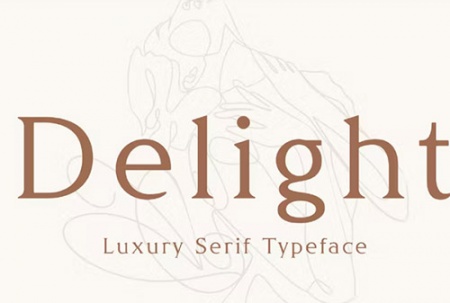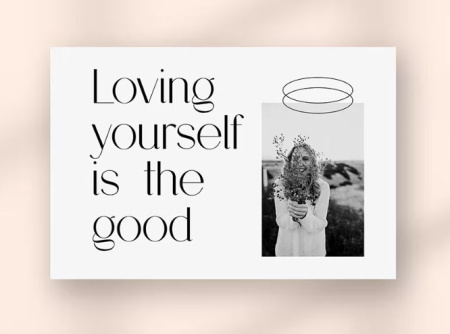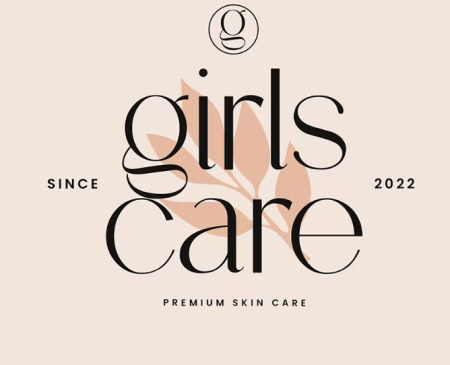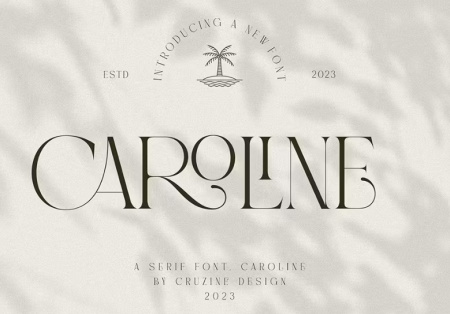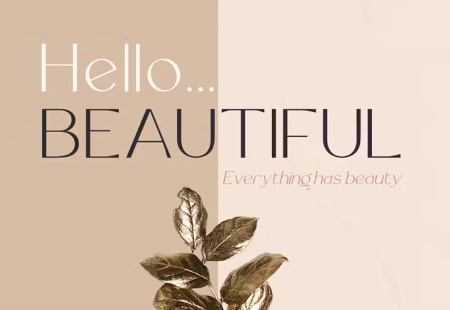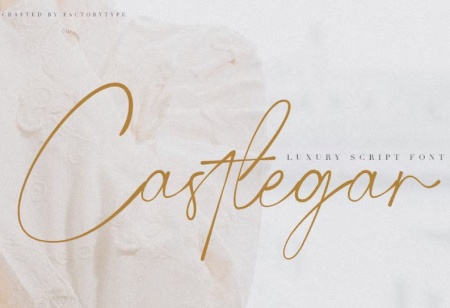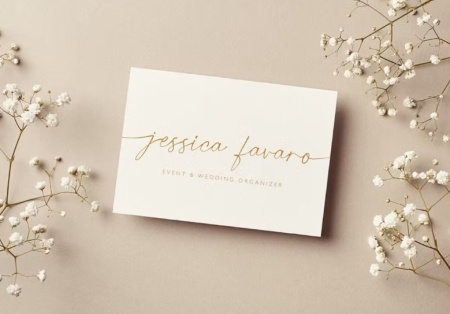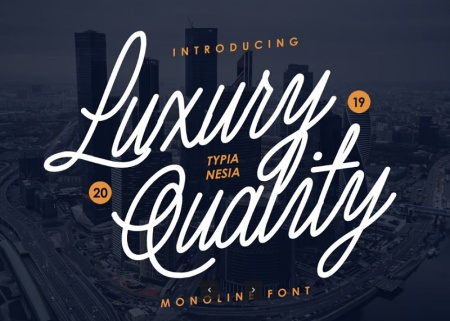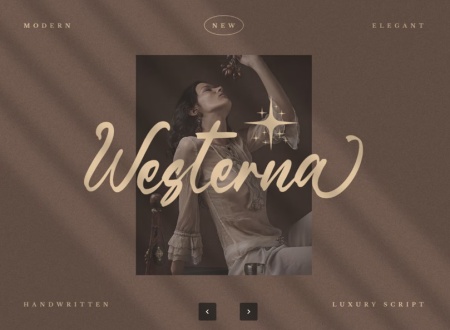
11 فونت لاکچری انگلیسی برای اینشات و کامپیوتر آپدیت جدید
دانلود فونت لاکچری انگلیسی Bonnevarc
در این پست از سایت gfx با معرفی یک فونت انگلیسی لاکچری جدید با نام Bonnevarc Luxury Sans Serif Font با شما همراه هستیم. فونت مدرن Serif که ظاهری زیبا، شیک و خاص دارد. این فونت لاکچری برای پروژههای مختلف مانند امضا، لوازم التحریر، لوگو، عروسی، نقل قولهای تایپوگرافی، جلد مجلات یا کتابها، سربرگهای وبسایت، لباس، برندسازی، طراحی بستهبندی و موارد دیگر کاملاً مناسب است. همچنین، برندسازی مرتبط با مد یا طراحی سرمقاله، ویژگیهای مردانه و زنانه را نشان میدهد. برای دانلود فونت لاکچری Bonnevarc به ادامه مطلب مراجعه کنید.
دانلود فونت انگلیسی ظریف و لاکچری Delight در جی اف ایکس دانلود
شما می توانید از فونت لاکچری Delight از آن برای تولید کارت تبریک تزئینی، جلد کتاب، نقل قول، پوستر، لوگو، کارت ویزیت، طرح عروسی، بسته بندی و موارد دیگر استفاده کنید.فونت انگلیسی Delight توسط یک طراح جوان ساخته شده است و اشتیاق او به تایپوگرافی در این فونت که تنها از چند حرف از الفبای استاندارد لاتین استفاده می کند، مشهود است. تنها با استفاده از خطوط برجسته و نازک و همچنین تغییرات ظریف در ضخامت، می توان از آن برای اهداف مختلف از جمله برندسازی، لوگو و پوستر استفاده کرد.فونت انگلیسی Delight یک فونت زیبا و در عین حال شیک و درجه یک است، بنابراین سعی کنید با وب سایت یا وبلاگ مد خود استفاده کنید و آن را شگفت انگیزتر و زیباتر کنید.
فونت لاکچری انگلیسی Oriella
فونت انگلیسی لاکچری دست نویس با نام Oriella Luxury Handwritten Font در جی اف ایکس دانلود. این فونت زیبا با تم لاکچری مناسب طراحی های مختلف می باشد. شما می توانید در اینشات و کامپیوتر از این فونت لاکچری استفاده کنید. فرمت های این فونت OTF،TTF و WOFF می باشد. این فونت لاکچری انگلیسی به صورت آپدیت به مطلب اضافه شده است. شما با تهیه اشتراک یا خرید تک فایل می توانید به تمامی فونت ها دسترسی داشته باشید.برای دانلود کارت ویزیت لاکچری به لینک مربوطه بروید.
دانلود فونت لاکچری انگلیسی برای اینشات
Rollgates Luxury یک فونت لوکس و زیبا است که هم به لحاظ کلاسیک ظریف و هم مدرن است. اگر به فونت لاکچری انگلیسی برای اینشات یا کامپیوتر نیاز دارید، پیشنهاد ما دانلود فونت لاکچری Rollgates می باشد. مناسب برای دعوت نامه های عروسی، پاورپوینت، انواع طراحی های گرافیکی، لوگو و هر طرحی که نیاز به ظاهری جذاب و لوکس دارد می باشد.
دانلود جدیدترین فونت های لاکچری انگلیسی
Castlegar Luxury، یکی دیگر از فونت های لاکچری انگلیسی به سبک دست نویس و لوکس می باشد. مناسب برای طراحی برند و لوگو، دعوتنامه عروسی، پستهای رسانههای اجتماعی و تبلیغات برند های لوکس می باشد.
دانلود فونت انگلیسی لوکس و لاکچری
در این مطلب با معرفی یک فونت لوکس به نام Glamoury با شما همراه هستیم. این فونت پر زرق و برق، سلطنتی، زیبا، کلاسیک مناسب برای استفاده برای عنوان، جلد، دعوت نامه، برچسب، پوستر، لوگو، نقل قول، بسته بندی محصول، سربرگ، کالا، رسانه های اجتماعی، کارت های تبریک و ... می باشد.
فونت انگلیسی لوکس و زیبا Luxury Quality
Luxury Quality یک فونت لوکس جدید زیبا است و برای طراحی های مدرن، برندسازی، لوازم التحریر، وبلاگ، تبلیغاتی ، دعوت نامه کارت، نقل قول هنری، رویدادهای خاص (عروسی، تولد، و غیره) و ... مناسب است. فونتهای انگلیسی لوکس و زیبا، با ظرافت و پیچیدگی خود، به طرحهای شما جلوهای مجلل و چشمنواز میبخشند.
فونت های لوکس انگلیسی جدید
Westerna یک فونت زیبا و لوکس با طراحی شیک است.فونت های لوکس انگلیسی جدید برای طراحی لوگوهای برندهای لوکس، محصولات گرانقیمت، کارت ویزیت، دعوتنامههای عروسی، مهمانیهای رسمی و غیره می باشد.
فونت لاکچری انگلیسی مناسب لوگو و پوستر
فونت لاکچری انگلیسی مناسب لوگو و پوستر، انتخابی ایده آل برای طراحانی است که به دنبال جلوه ای متفاوت و حرفه ای در آثار خود هستند. این مطلب شامل فونت لاکچری انگلیسی برای طراحان گرافیک با طراحی ظریف، مدرن و چشمگیر است که می تواند برند شما را ارتقا دهد. چه در حال طراحی یک لوگوی مینیمال باشید و چه پوستر های تبلیغاتی شیک، این فونت جلوه ای لوکس و خاص به پروژه های شما می بخشند. استفاده از این فونت ها، حس اعتبار، کیفیت و زیبایی را به مخاطب منتقل کرده و باعث میشود طراحی شما ماندگارتر به نظر برسد.
دانلود فونت لاکچری و شیک انگلیسی برای طراحی های حرفه ای
اگر برای طراحی پوستر، لوگو، کارت دعوت، پست اینستاگرام یا پروژه های گرافیکی خاص به دنبال یک تایپ فیس متفاوت هستید، دانلود فونت لاکچری انگلیسی می تواند ظاهر طراحی شما را حرفه ای تر و چشمگیرتر کند. فونت های انگلیسی لوکس معمولاً با فرم های ظریف، کشیده و جذاب طراحی می شوند و برای پروژه هایی با سبک کلاسیک، مینیمال و لاکچری کاربرد زیادی دارند. با استفاده از این فونت ها می توانید متن لاکچری انگلیسی با فونت زیبا ایجاد کنید و برای عنوان ها، نوشته های تبلیغاتی، طراحی برند، بسته بندی و محتوای شبکه های اجتماعی ظاهری خاص داشته باشید.
ویژگی های فونت لاکچری انگلیسی از جی اف ایکس دانلود
✅ شامل 11 فونت لاکچری انگلیسی ✅ نام فونت انگلیسی 1: Bonnevarc ✅ نام فونت انگلیسی 2: Delight ✅ نام فونت انگلیسی 3: Oriella ✅ نام فونت انگلیسی 4: Caroline Luxury ✅ نام فونت انگلیسی 5: Rollgates Luxury ✅ نام فونت انگلیسی 6: Castlegar Luxury ✅ نام فونت انگلیسی 7: Glamoury - Luxury ✅ نام فونت انگلیسی 8: Luxury Quality ✅ نام فونت انگلیسی 9: Westerna - Luxury Font
✅ نام فونت انگلیسی 10: Top Luxury - Luxury Modern Classy Font